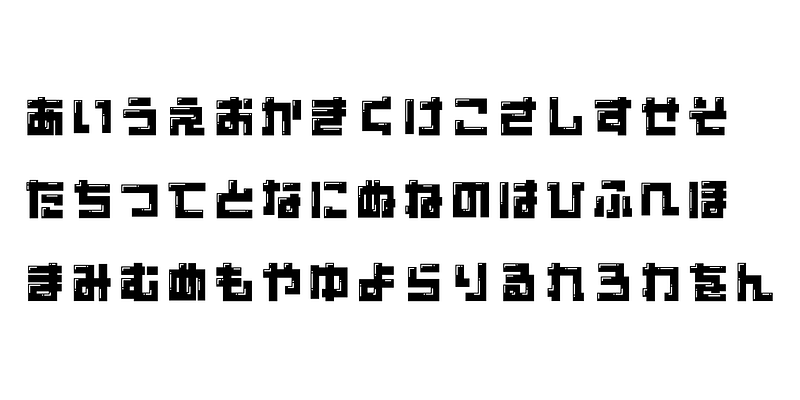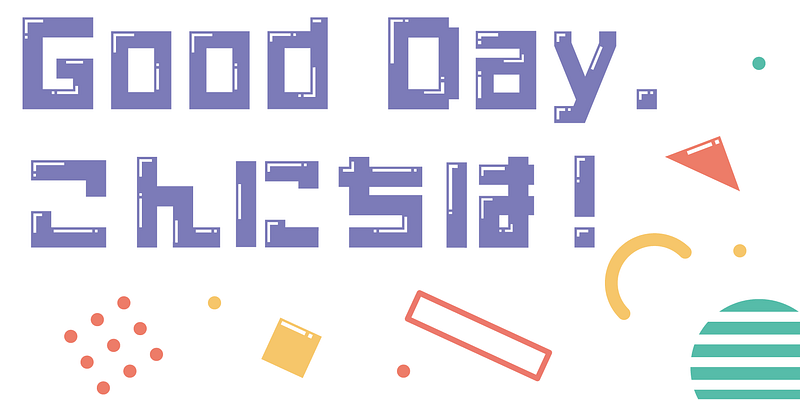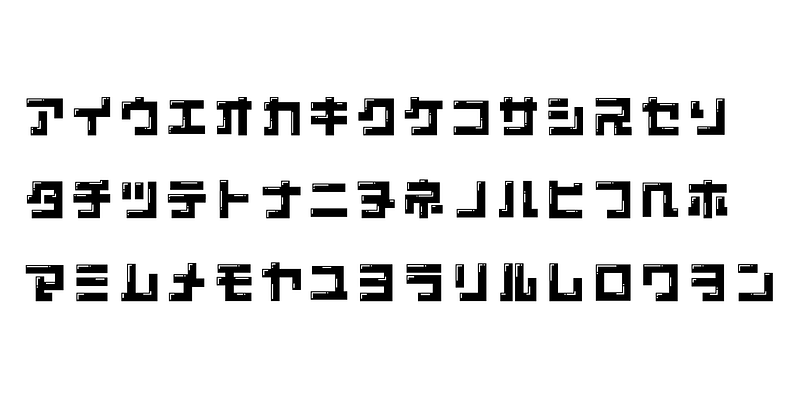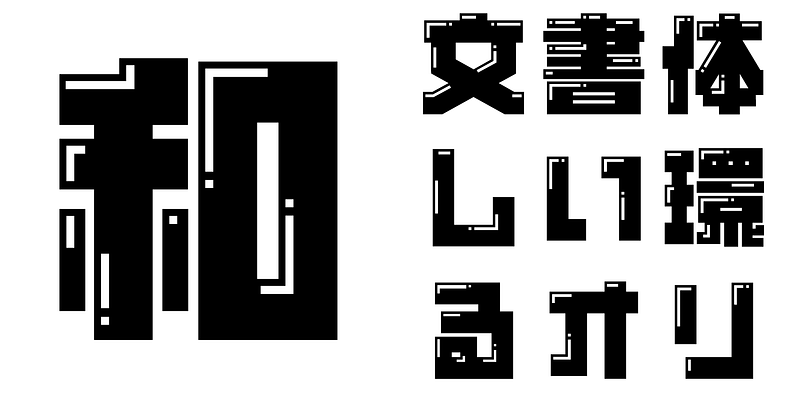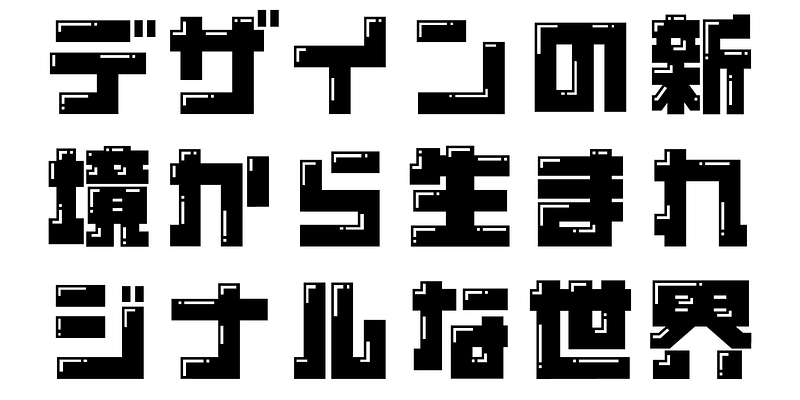
Dies basiert auf dem Design von AB-DON.
Hervorgehobene Bereiche in Weiß werden hinzugefügt, um einen 3D-Effekt zu erzielen. Diese Schrift eignet sich für Display-Zwecke, die in größeren Schriften erstellt werden, um ein Ausfüllen der hervorgehobenen Bereiche zu vermeiden.
Diese Schrift enthält die 1.000 beliebtesten Kanji-Zeichen, die aus Zeichenhäufigkeitstabellen von Zeitungsunternehmen, Verlagen und Sprachforschungsinstituten ausgewählt wurden, sowie 206 Kana-Zeichen und Interpunktionszeichen.
In der heutigen japanischen Schriftproduktion gelten die 7.000 Zeichen des JIS-Standards als unabdingbar. Aber brauchen alle Schriften wirklich 7.000 Zeichen? Im Zeitalter des Fotosatzes wurden weit weniger Zeichen benötigt. FONT1000, eine Gruppe unabhängiger Schriftdesigner, ging von dieser einfachen Frage aus. Wir haben die mindestens 1.000 (ideografischen) Kanji-Zeichen ausgewählt, die für den Satz in Japanisch erforderlich sind, und aktiv Schriften und Schriftbilder dafür entworfen. Dieser 1000-Kanji-Zeichensatz wurde unter Verwendung von Zeichenhäufigkeitsdaten ausgewählt, die u. a. von Zeitungsunternehmen, Verlagen und Sprachforschungsinstituten zusammengestellt wurden, und enthält auch Kana-Silbenzeichen und Satzzeichen. FONT1000 begann 2001 mit 25 Designern und 25 Schriften. Heute haben wir 130 Schriften und sind auf fast 40 Mitglieder angewachsen, sodass wir an Schriften mit mehr Zeichen arbeiten können.